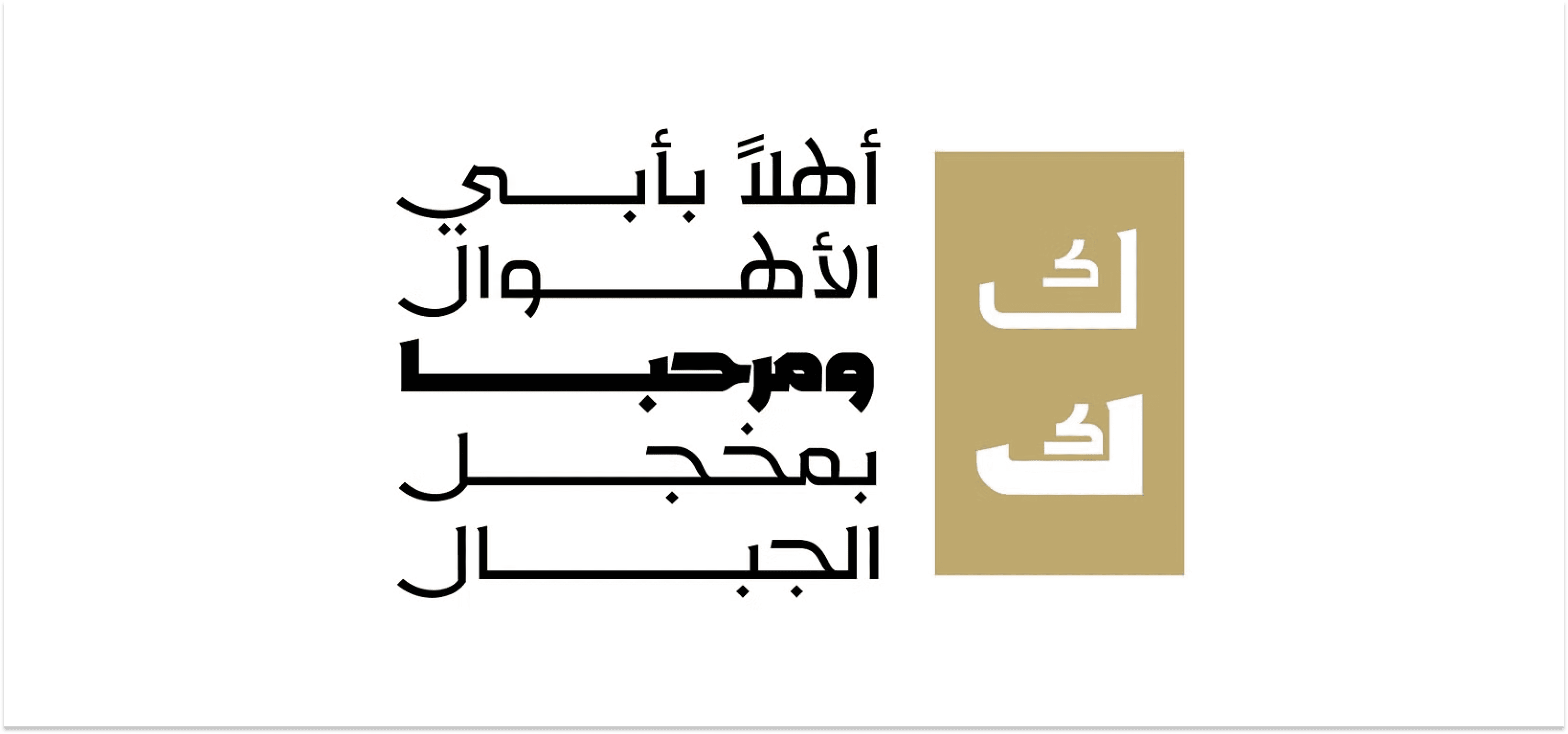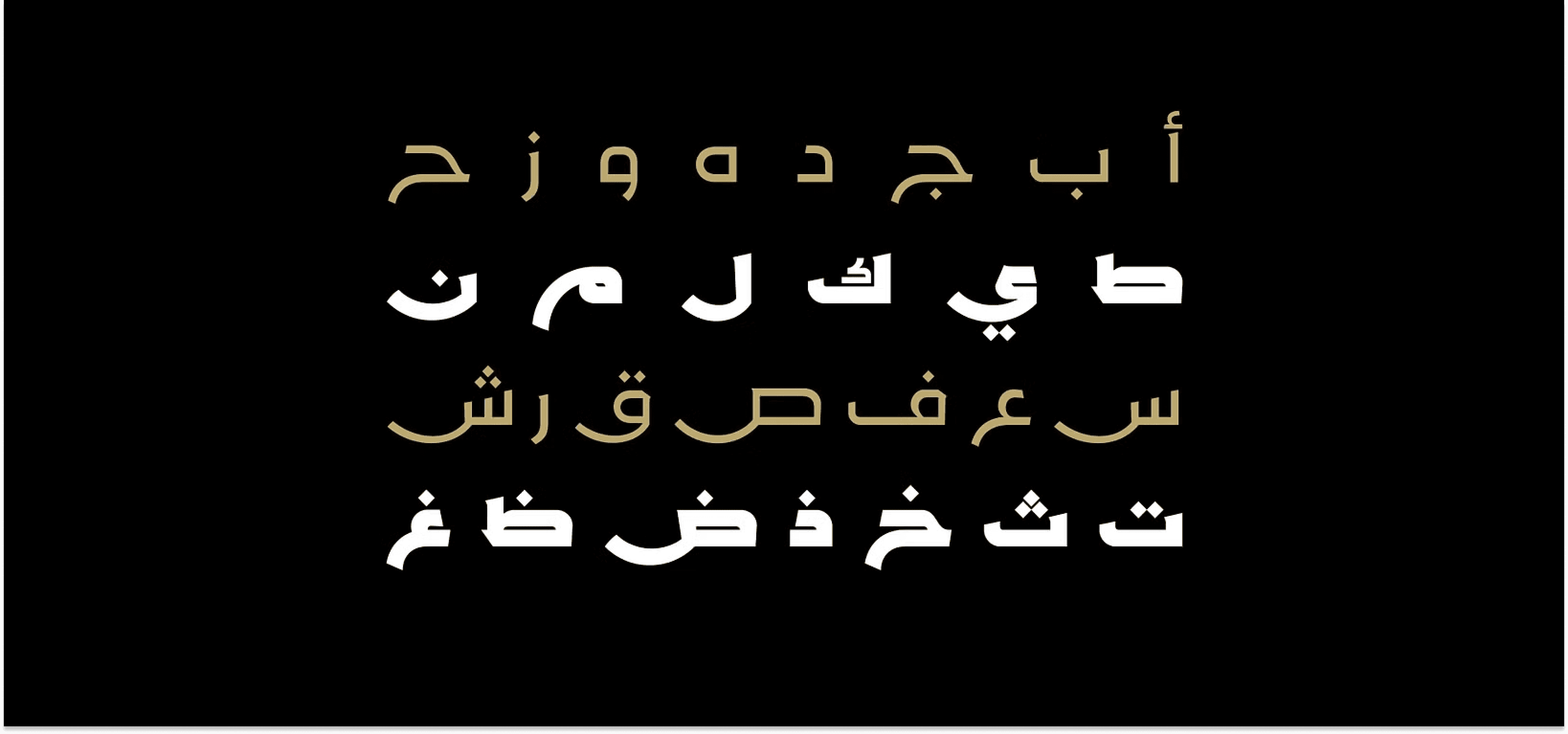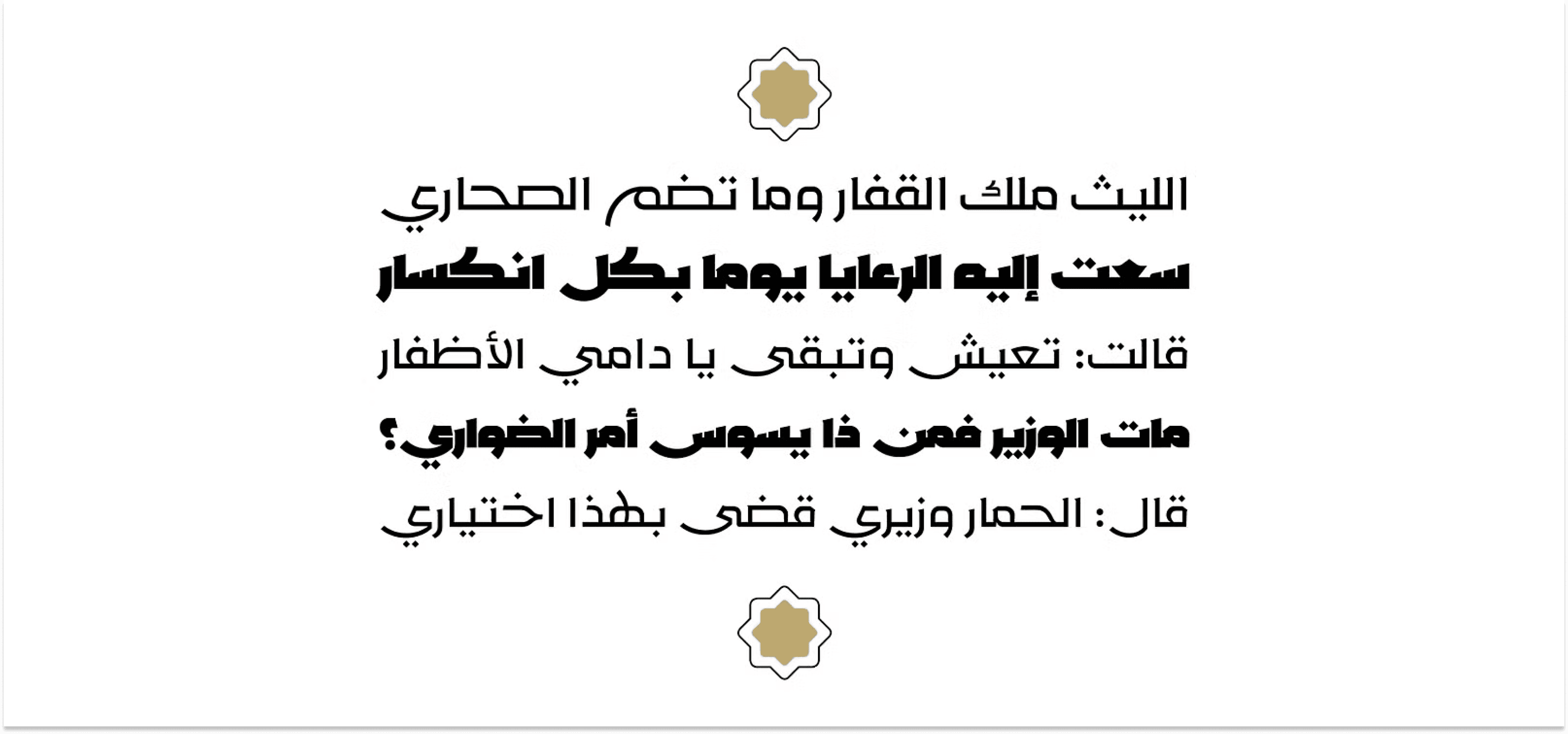
خط Rakan (وهي كلمة عربية تعني "الوقور" أو "الرزين") هو خط عرض عربي يتميز بتصميم حديث مستوحى من الخط الكوفي، يجمع بين البساطة والبنية القوية للحروف. يتوفر الخط بوزنين: عادي (Regular) وعريض (Bold)، مما يجعله مناسبًا لتطبيقات التصميم المعاصرة مثل الإعلانات، العلامات التجارية، وتصميم المطبوعات.